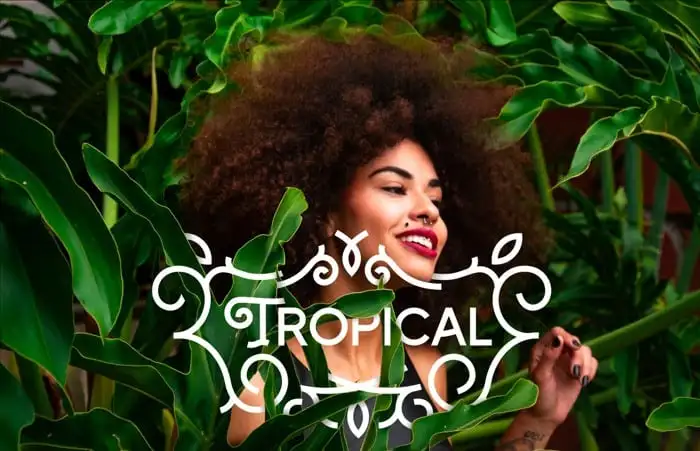
Zilap Nature Sans Serif Font – Download Grátis
A Zilap Nature Sans Serif Font é uma escolha perfeita para designers que buscam incorporar a elegância natural no seu trabalho. Essa fonte vintage monoline se destaca por sua simplicidade e sofisticação, sendo ideal tanto para uso em headlines quanto na criação de logos e marcas modernas. ZILAP ZP criou essa tipografia inspirada na harmonia da natureza, enfatizando a beleza dos elementos naturais em linhas simples e elegantes que tornam sua aparência moderna e sofisticada. A Zilap Nature Sans Serif Font vem equipada com um conjunto de ornamentos complementares ao estilo de design. Esses detalhes adicionais são perfeitos para enriquecer a estrutura da fonte, oferecendo a opção de personalizar seu uso em qualquer projeto que necessite de destaque visual. Seja para embalagens de produtos, peças de arte ou materiais promocionais – a Zilap Nature Sans Serif Font é uma escolha sólida e criativa para quem busca combinar elegância e naturalidade no design.